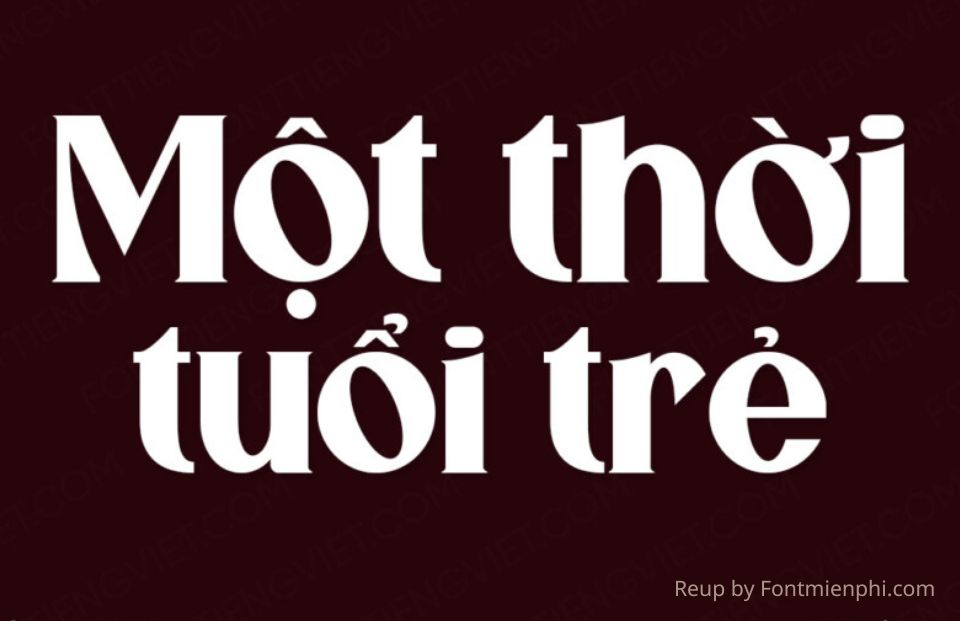
Font Việt Hóa 1FTV VIP Lumiare: Lựa Chọn Hoàn Hảo Cho Thiết Kế Sang Trọng
Font Việt hóa 1FTV VIP Lumiare đang là một trong những kiểu chữ được cộng đồng designer săn đón mạnh mẽ nhất hiện nay. Với đường nét thanh lịch, sang trọng cùng bộ dấu tiếng Việt được xử lý tỉ mỉ, đây chính là “vũ khí bí mật” giúp các ấn phẩm thiết kế của bạn thăng hạng tức thì.
1. Tổng quan về Font Việt hóa 1FTV VIP Lumiare
Lumiare vốn nổi tiếng là một typeface mang đậm phong cách hiện đại, tinh tế và phảng phất nét cổ điển đầy quyến rũ. Tuy nhiên, việc sử dụng font gốc thường gặp trở ngại lớn về lỗi hiển thị dấu khi gõ tiếng Việt.
Nhận thấy nhu cầu đó, đội ngũ 1FTV (1FontTV) đã tiến hành Việt hóa và cho ra mắt phiên bản 1FTV VIP Lumiare. Chữ “VIP” trong tên gọi đã khẳng định chất lượng cao cấp của bản Việt hóa này:
• Kerning (khoảng cách giữa các chữ) được tinh chỉnh hoàn hảo.
• Bộ dấu tiếng Việt được vẽ lại thủ công, đồng điệu tuyệt đối với đường nét của phông chữ gốc.
• Tối ưu hóa hiển thị trên cả nền tảng web lẫn in ấn.
2. Đặc điểm nổi bật của 1FTV VIP Lumiare
Không phải ngẫu nhiên mà font 1FTV VIP Lumiare lại được giới thiết kế đồ họa ưa chuộng đến vậy. Dưới đây là những ưu điểm vượt trội:
• Đường nét thanh thoát, sang trọng: Lumiare sở hữu độ tương phản nét thanh – nét đậm (thick and thin strokes) cực kỳ ấn tượng, mang lại cảm giác đắt tiền và cao cấp cho người xem.
• Dấu tiếng Việt chuẩn xác: Đội ngũ 1FTV nổi tiếng với kỹ thuật Việt hóa “có tâm”. Các dấu thanh (huyền, sắc, hỏi, ngã, nặng) hay dấu mũ (â, ê, ô) đều được đặt ở vị trí vừa vặn, không bị lẹm hay rời rạc.
• Hỗ trợ tính năng OpenType: Nếu bạn sử dụng các phần mềm thiết kế chuyên dụng như Adobe Illustrator hay Photoshop, bạn có thể kích hoạt các ký tự thay thế (Alternates) hoặc nét lượn (Swashes) để làm chữ ký hoặc tiêu đề thêm phần mềm mại.
3. Ứng dụng thực tế trong thiết kế
Với phong cách “Luxury” đặc trưng, Font Việt hóa 1FTV VIP Lumiare phát huy sức mạnh tối đa trong các dự án sau:
Thiết kế nhận diện thương hiệu
Tuyệt vời để làm Logo, Slogan cho các thương hiệu thời trang cao cấp, spa, mỹ phẩm, trang sức hoặc các dự án bất động sản hạng sang.
Ấn phẩm cưới (Wedding Invitation)
Tên cô dâu chú rể hoặc tiêu đề thiệp mời sẽ trở nên vô cùng lãng mạn, thanh lịch và mang đậm phong cách Fine Art khi sử dụng font chữ này.
Thiết kế bao bì (Packaging) & Editorial
Rất phù hợp để làm điểm nhấn trên bao bì sản phẩm (hộp nước hoa, chai rượu vang) hoặc làm tiêu đề (Headline) cho các tạp chí thời trang, lifestyle.
Nếu bạn đang tìm kiếm một phông chữ để nâng tầm các dự án thiết kế cao cấp của mình, Font Việt hóa 1FTV VIP Lumiare chắc chắn là một mảnh ghép không thể thiếu trong thư viện đồ họa của bạn. Sự kết hợp giữa đường nét nguyên bản tuyệt đẹp và kỹ thuật Việt hóa hoàn hảo của 1FTV sẽ giúp bạn tiết kiệm thời gian mà vẫn tạo ra những tác phẩm mãn nhãn.